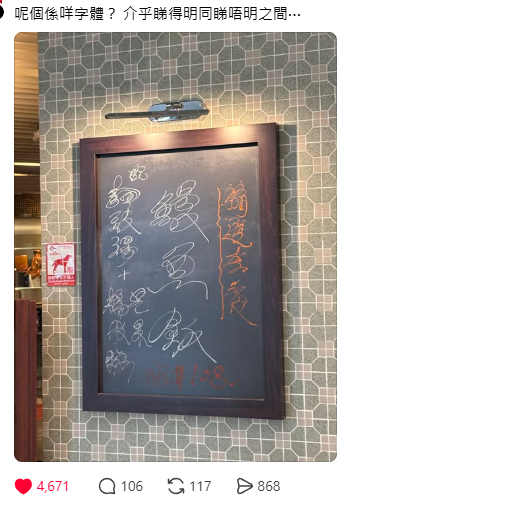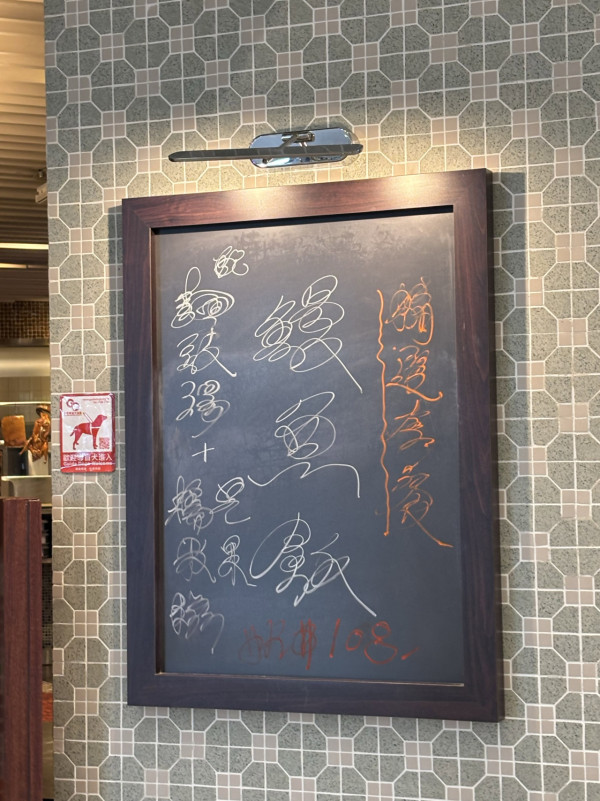
茶餐廳神級餐牌全連筆爆紅!網民競猜內容驚嘆神奇:睇得明先有資格食
【茶餐廳 / 茶餐廳餐牌 / 一筆畫字體 / Threads熱話 / 港灣茶餐廳 / 灣仔美食 / 全連筆書法】講到茶餐廳餐牌,大家第一時間諗起的可能是茶餐廳夥計難解的「火星文」手寫單,但最近一間位於灣仔的茶餐廳竟然玩出新高度。一張餐牌中文字全部由頭連到尾,一筆畫勾勒出極具設計感的字體,瞬間在Threads 爆紅瘋傳!不少網民驚嘆好神奇、「吸到睛又唔會睇唔明」。到底呢個神級餐牌寫了什麼?即睇下文,看看自己睇唔睇得明餐牌點餐!
Threads 瘋傳茶餐廳餐牌變身「現代藝術品」
在茶香港茶餐廳,夥計手寫的手寫單就見得多,手寫餐牌已經越來越罕見。然而一間茶餐廳仍堅持手寫餐牌,更在 Threads 上瘋傳?因為照片中的所有的中文字都由一條線流暢地由頭連到尾,完全沒有中途提筆,令網民忍不住發問「呢個係咩字體」?這種「一筆畫」的字體介乎睇得明與睇唔明之間,令平平無奇的一塊茶餐廳手寫板,瞬間變成藝術品一樣,引起網民熱議。
網民熱議:睇得明先神奇
這塊手寫餐牌在Threads上爆紅之後,不少人都紛紛留言一起網上競猜到底牌上寫了什麼。大家對於這種創新字體幾乎一面倒給予好評,因為一般一筆畫字體很容易變得一團亂,但有網民驚嘆「好神奇,第一眼以為自己睇唔明,睇睇下又明」、「吸到睛但係又唔會睇唔明,其實寫得幾好」,大讚絕對是餐廳墨寶嚟,欣賞店員創意。
餐牌內容開估!揭茶餐廳真身
經過一輪競猜後,絕大部分網民都成功估中內容,就是「精選套餐:鰻魚飯 配麵豉場+芒果糯米糍」,有人更幽默留言「鰻魚體」、「吃精選套餐一定要經歷考驗,咁易食到點得」。有網民更因為這塊茶餐廳獨家餐牌,直言想去觀摩一下,就算路過都想停低研究,無形中為餐廳帶來極高曝光率。據樓主分享,這塊餐牌就是位於會展的港灣茶餐廳。